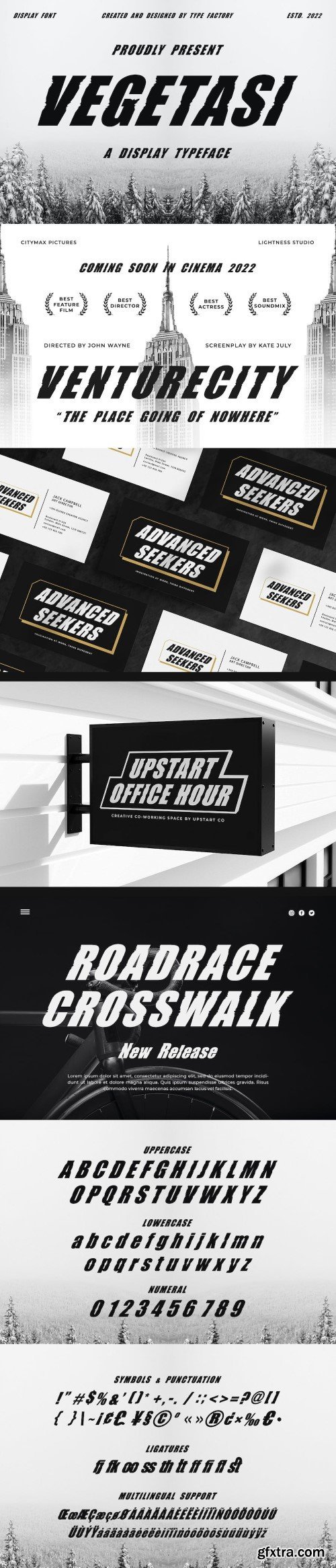
植被 - 一种显示类型face
Vegetasi ist eine Display-Schrift, die sorgfältig von Hand gefertigt wurde, um ein echter Favorit zu werden. Ihr lässiger Charme lässt sie wunderbar bodenständig, lesbar und letztlich unglaublich vielseitig wirken. Diese Schriftart wird in jedem Kontext hervorragend aussehen, egal ob sie auf geschäftigen Hintergründe oder als eigenständige Überschrift verwendet wird, insbesondere monochrom im Design!
Eigenschaften:
- Großbuchstaben
- Kleinbuchstaben
- Symbole und Interpunktion
- Zahl
- Ligatur
- Alternate
- Mehrsprachiger Support